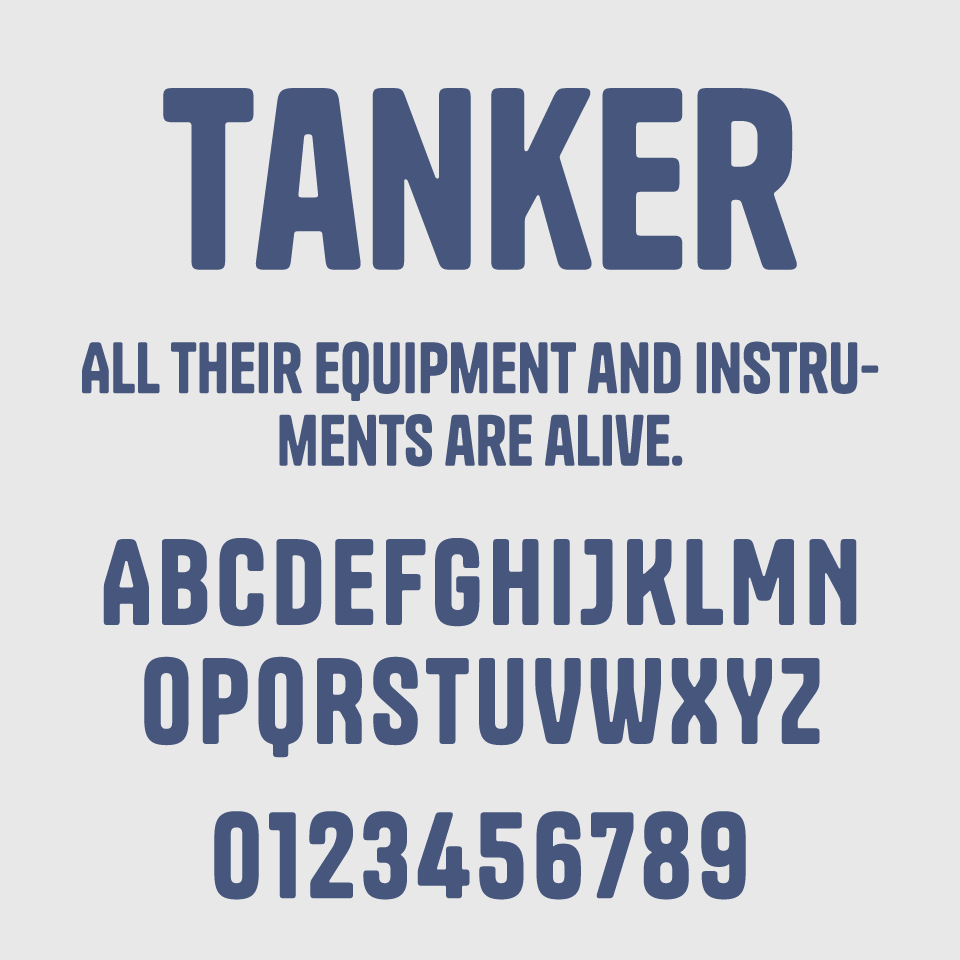
Tankerフォントは、ミリタリーテイストとヴィンテージ感が交差する、無骨で頼もしい存在感のあるサンセリフフォントです。
どっしりとした文字幅と、角をわずかに丸めたディテールが、厳つさの中に程よい親しみやすさを添えています。整然としながらも、カチッとしすぎない柔らかい印象が、工業系やアウトドアブランドなどにもよくなじみます。
ワークウェアのタグや、レトロなアメリカンガレージを連想させる雰囲気があり、印刷物やロゴに使用すると一気にムードが出ます。タフでありながら、角丸でちょっぴり可愛さのあり遊び心も忘れないフォントです。
収録文字は、大文字/数字/記号の収録となっています。